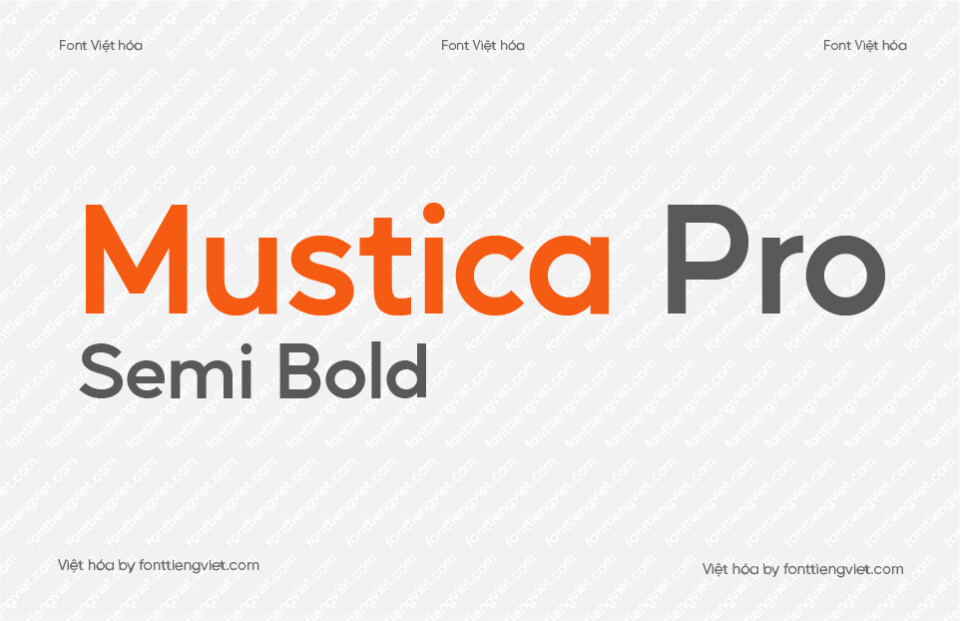
Font Việt hóa 1FTV VIP Mustica Pro Semi Bold
Trong thế giới thiết kế đồ họa hiện đại, việc lựa chọn một bộ Font Miễn Phí chất lượng luôn là ưu tiên hàng đầu của các nhà sáng tạo. Đặc biệt, bộ Font Việt hóa 1FTV VIP Mustica Pro Semi Bold đã trở thành một hiện tượng trong cộng đồng thiết kế Việt Nam nhờ sự kết hợp hoàn mỹ giữa nét thanh lịch cổ điển và hơi thở hiện đại. Đây là một phiên bản được tinh chỉnh kỹ lưỡng về dấu tiếng Việt, giúp người dùng không còn lo lắng về lỗi hiển thị khi soạn thảo văn bản hay làm tiêu đề quảng cáo. Với độ dày Semi Bold vừa phải, bộ font này tạo nên sự cân bằng tuyệt vời, không quá mỏng manh nhưng cũng không quá nặng nề, phù hợp cho nhiều mục đích sử dụng khác nhau từ in ấn đến hiển thị trên nền tảng số.
Khám phá vẻ đẹp đặc trưng của Font Việt hóa 1FTV VIP Mustica Pro Semi Bold
Cấu trúc hình học hiện đại và linh hoạt
Font Việt hóa 1FTV VIP Mustica Pro Semi Bold được xây dựng dựa trên các tỷ lệ hình học chuẩn xác, mang lại cảm giác vững chãi và chuyên nghiệp. Mỗi đường nét trong bộ font đều được trau chuốt tỉ mỉ, giúp văn bản trở nên dễ đọc ngay cả ở kích thước nhỏ. Điểm mạnh của phiên bản Semi Bold chính là khả năng tạo điểm nhấn cực tốt mà vẫn duy trì được sự tinh tế cần thiết cho tổng thể bản thiết kế. Điều này giúp các bạn học sinh, sinh viên dễ dàng ứng dụng vào việc làm bài thuyết trình hoặc thiết kế bìa báo cáo học tập thêm phần sinh động và bắt mắt hơn.
Khả năng tương thích và hỗ trợ tiếng Việt hoàn hảo
Một trong những lý do khiến Font Việt hóa 1FTV VIP Mustica Pro Semi Bold được săn đón chính là hệ thống dấu tiếng Việt được thiết kế vô cùng tự nhiên. Các dấu thanh như sắc, huyền, hỏi, ngã, nặng được đặt ở vị trí hợp lý, không làm thay đổi khoảng cách dòng hay gây rối mắt. Sự đồng nhất giữa các ký tự gốc và các ký tự có dấu giúp đoạn văn bản trở nên liền mạch và chuyên nghiệp hơn hẳn các bộ font thông thường khác trên thị trường hiện nay.
Ứng dụng thực tiễn của Font Việt hóa 1FTV VIP Mustica Pro Semi Bold trong thiết kế
Lựa chọn hàng đầu cho thiết kế thương hiệu và quảng cáo
Nhờ vẻ ngoài hiện đại và sang trọng, Font Việt hóa 1FTV VIP Mustica Pro Semi Bold thường xuyên được các nhà thiết kế lựa chọn để làm logo, banner quảng cáo hoặc tiêu đề cho các chiến dịch truyền thông. Độ đậm của font giúp các thông điệp chính trở nên nổi bật và thu hút thị giác ngay từ cái nhìn đầu tiên. Ngoài ra, nó còn rất phù hợp để làm typography cho các poster phim, bìa sách hoặc tạp chí thời trang cao cấp.
Sáng tạo nội dung trên mạng xã hội và website
Trong kỷ nguyên số, việc trình bày nội dung trên Facebook, Instagram hay Website đòi hỏi sự rõ ràng và phong cách. Font Việt hóa 1FTV VIP Mustica Pro Semi Bold đáp ứng tốt yêu cầu này bằng khả năng hiển thị sắc nét trên mọi loại màn hình. Bạn có thể sử dụng font này để thiết kế các câu trích dẫn (quotes), hình ảnh minh họa cho blog cá nhân hay các bảng tin của nhà trường, tạo nên một giao diện thân thiện và chuyên nghiệp đối với người xem.